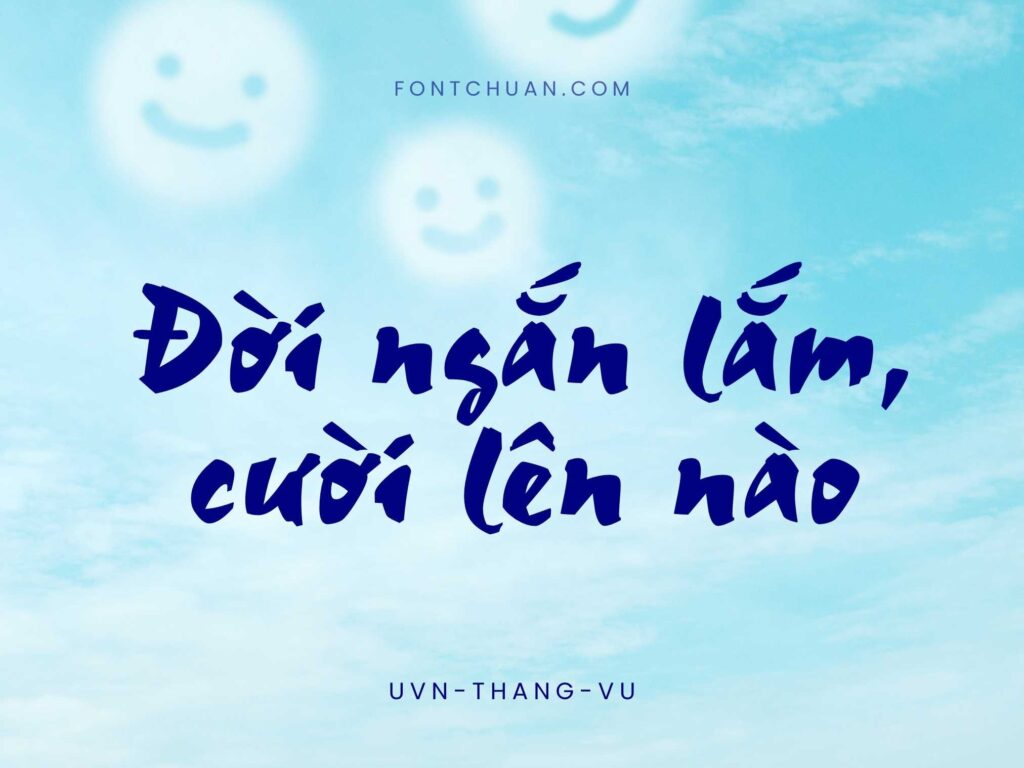
Font UVN Thang Vu Việt Hóa
UVN Thằng Vũ là một phông chữ thư pháp mang phong cách nghệ thuật viết tay truyền thống. Được thiết kế với các nét bút lông mềm mại và uyển chuyển, phông chữ này tạo nên sự thanh thoát và tinh tế cho các tác phẩm thiết kế. UVN Thằng Vũ hỗ trợ đầy đủ các ký tự tiếng Việt, giúp người dùng dễ dàng sử dụng trong các dự án sáng tạo liên quan đến văn hóa Việt Nam.
Với thiết kế độc đáo và nghệ thuật, UVN Thằng Vũ phù hợp cho các ứng dụng như thiệp mời, tiêu đề sách, thiết kế logo và các ấn phẩm nghệ thuật. Trong lĩnh vực sự kiện, phông chữ này có thể được sử dụng trong các dịp như lễ hội, lễ cưới và các sự kiện văn hóa. Ngoài ra, nhờ khả năng đọc dễ dàng và nét chữ uyển chuyển, UVN Thằng Vũ còn là một Font chữ giáo dục lý tưởng, phù hợp để thiết kế sách giáo khoa, bài giảng, tài liệu học tập và các ấn phẩm giáo dục, giúp nội dung trở nên sinh động và dễ tiếp nhận.